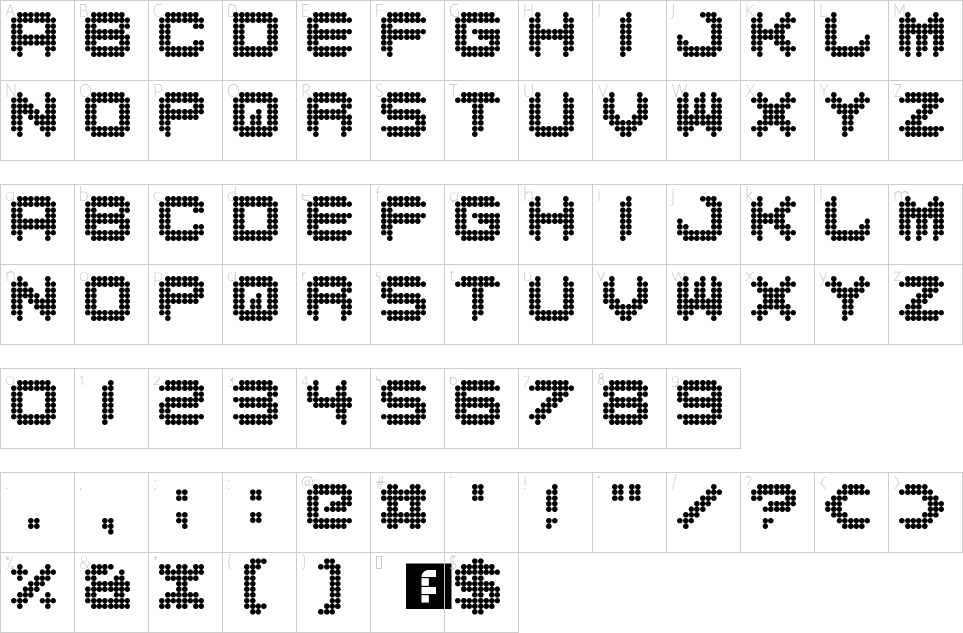
Descubra a fonte Dance Floor para seus projetos digitais no formato Windows e Mac. Desenvolvida pelo designer Chequered Ink, esta font foi baixada mais de 14.600 vezes até agora. Perfeita para ambientes onde há uma forte ênfase na movimentação visual como discotecas ou espaços de entretenimento, a Dance Floor oferece um estilo vibrante e fácil de ler que se assemelha à atmosfera pulsante desses locais. Seja para criar cartazes de eventos, design gráfico ou até mesmo letras musicais nos teclados, esta font adquirem um toque especial ao seu projeto.